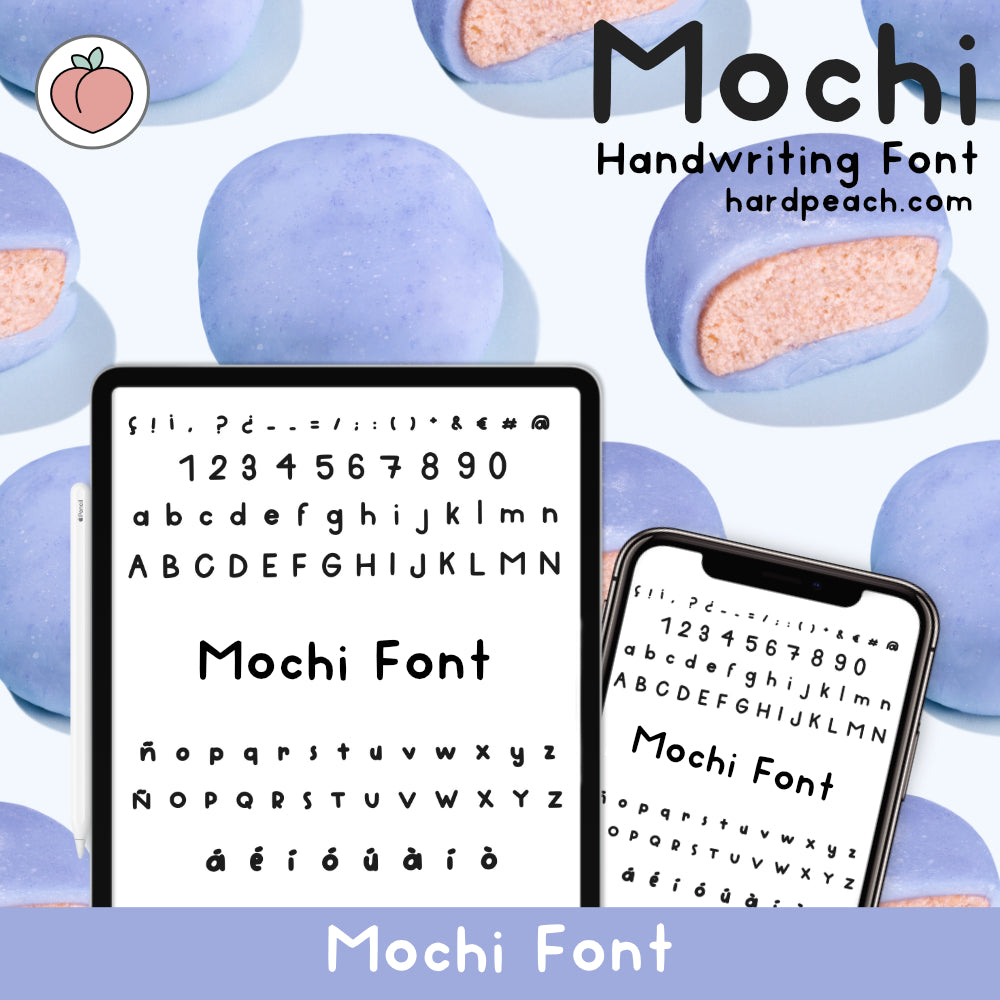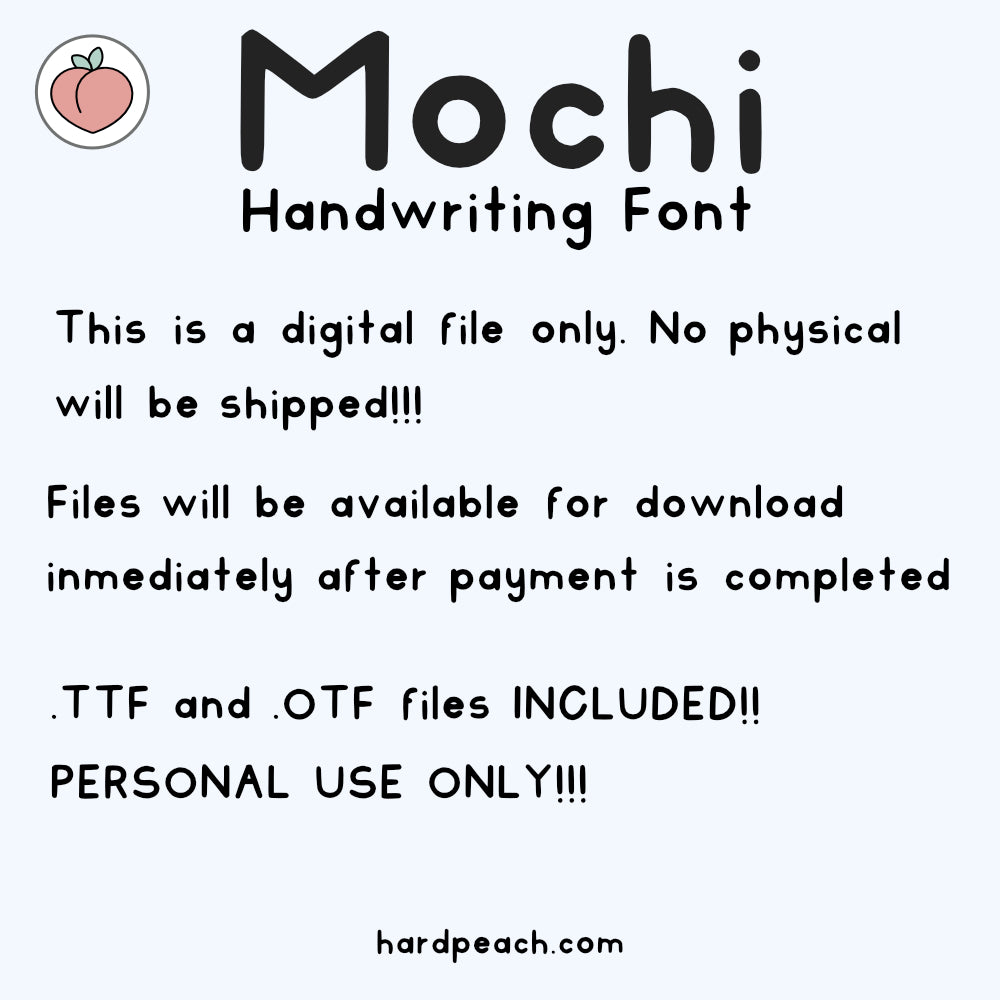
MOCHI HANDWRITTEN FONT
¡Perfecta para notas en inglés, español...!
Esta fuente incluye todos los caracteres principales: mayúsculas, minúsculas, números, vocales con acentos (español), y acentos abiertos (à) y signos. Además, incluye los acentos y las letras ñ y ç.